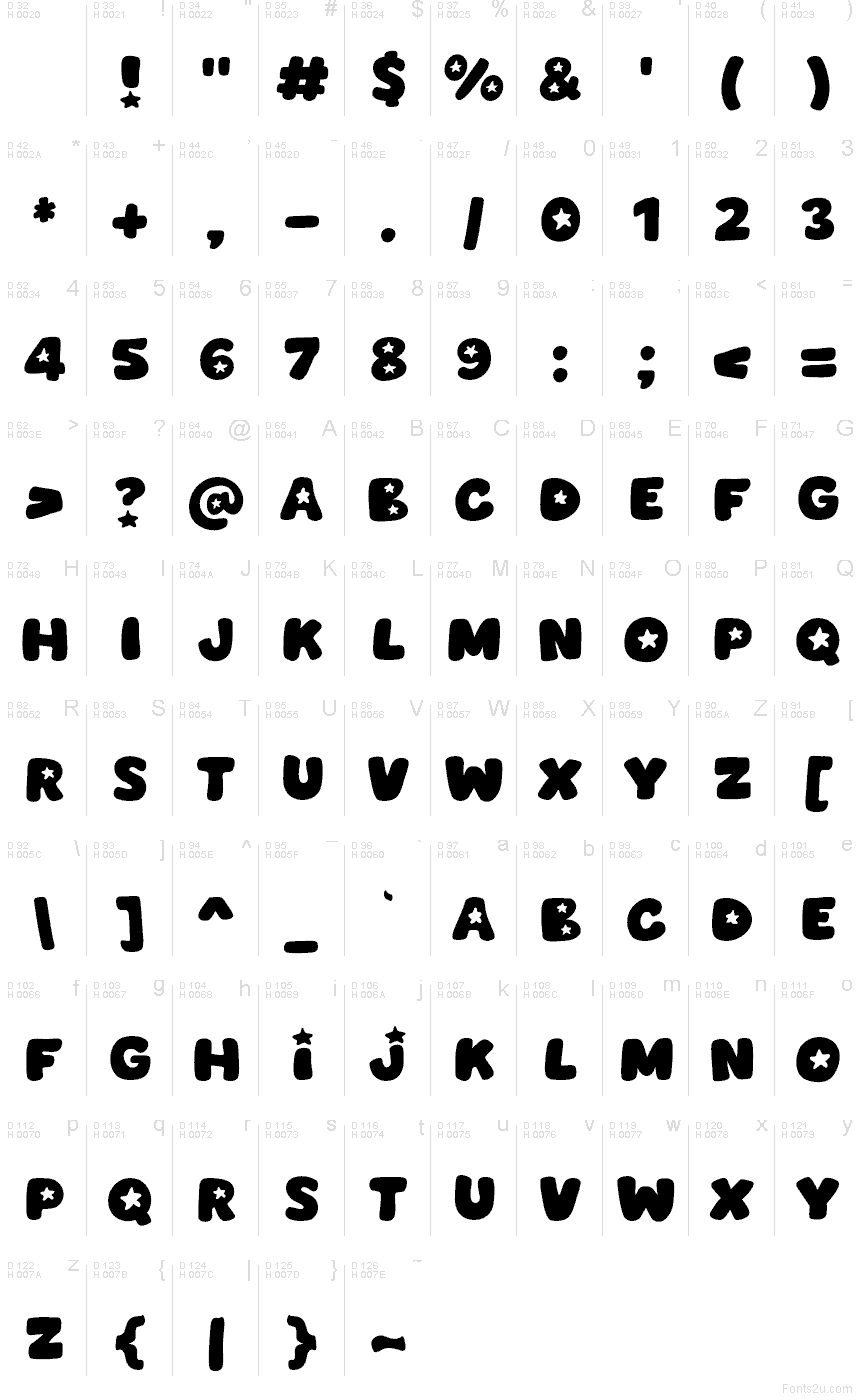
Singsong di MJType è un font display gratuito in stile cartoon, con lettere morbide e gonfie e un aspetto vivace che sembra uscito direttamente da un titolo per bambini. Le sue forme tozze, gli angoli arrotondati e la "i" con la stellina conferiscono al font un carattere manuale e gioioso, mentre le curve ampie rendono le parole semplici e d'impatto.
Questo font gratuito è perfetto per packaging allegri, etichette di snack, poster scolastici, inviti di compleanno e miniature di YouTube, dove un tono leggero e giocoso conta più della perfezione. Funziona bene anche per titoli brevi, copertine e loghi, poiché le lettere appaiono gonfie e animate senza risultare confuse.